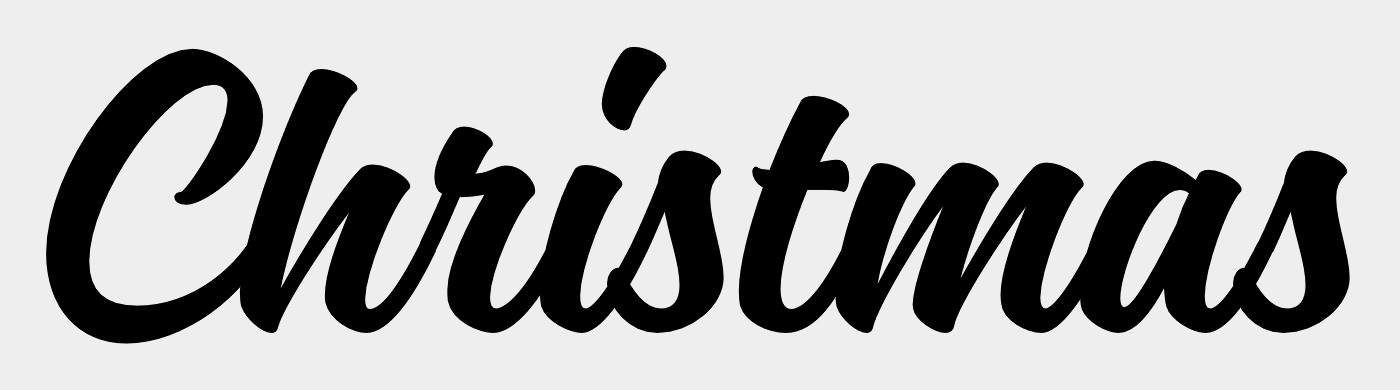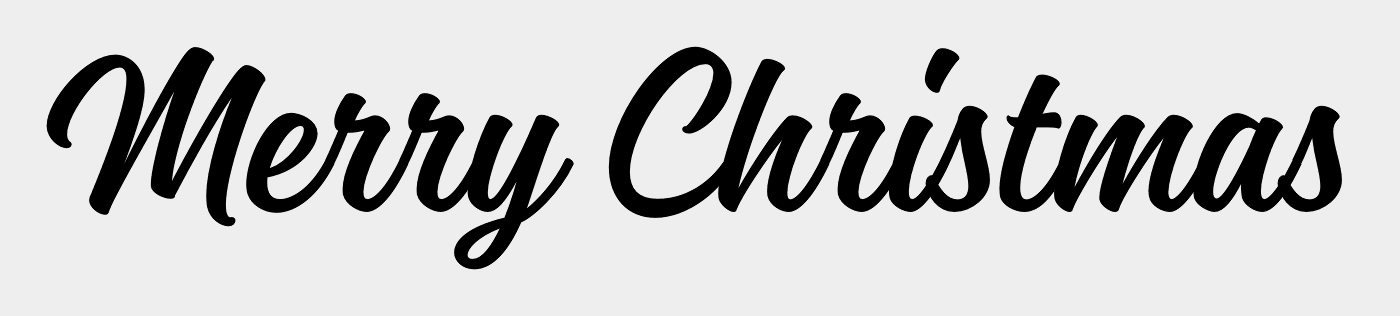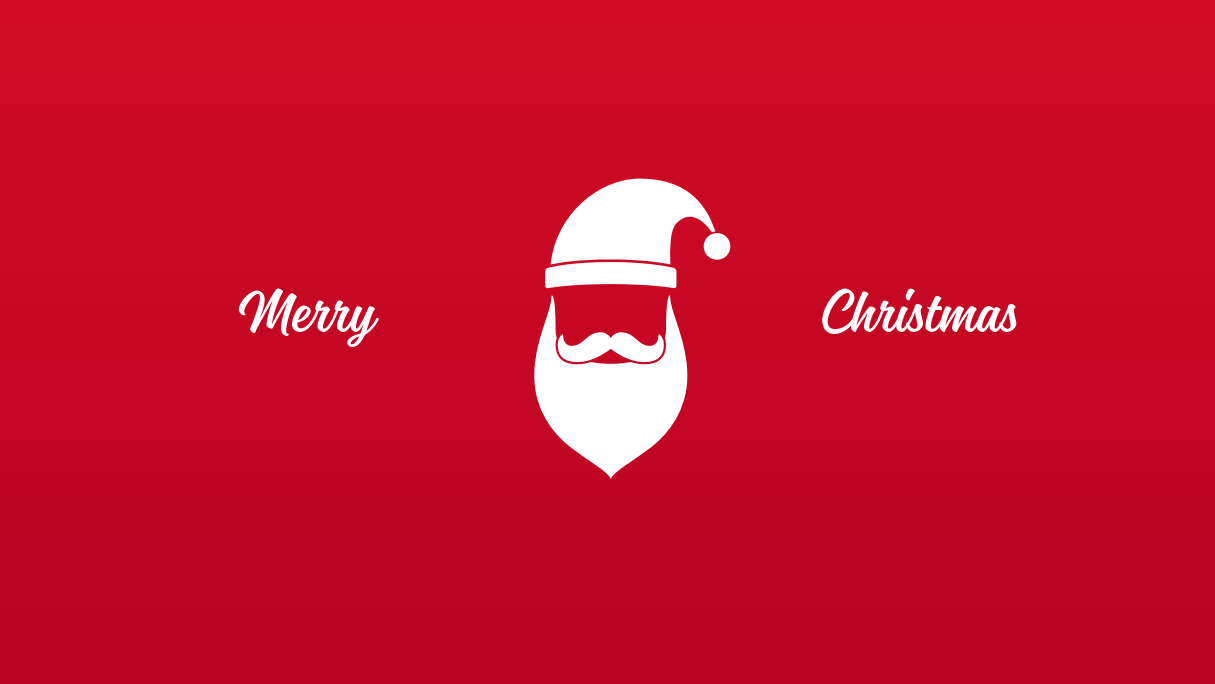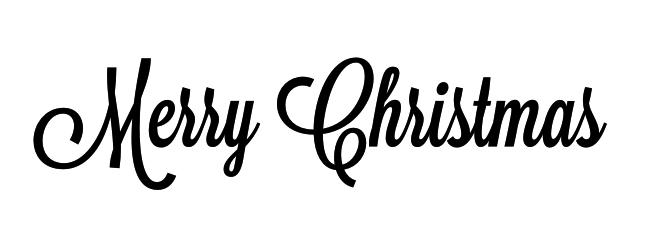
Weihnachts-Font Viktor Script (Alternativen)
Ich bin gerade verzweifelt auf der Suche nach einem ähnlichen Font zur Viktor Script.
Kennt jemand von euch gute (kostenlose) Alternativen zur Viktor-Script im ähnlichen Schreibstil :-??
Ich könnte ja mal wieder Frau Worthington ins Spiel bringen: https://www.fontsquirrel.com/fonts/milkshake
Ist allerdings etwas breiter …
Ansonsten findet man solche Schriften doch gerade wie Sand am Meer :-?
Warum passt denn die Viktor nicht, bzw. wozu Alternativen?
Ich habe bis jetzt noch keine passende bzw. gute Alternative gefunden :-(.
Passt etwas in dieser Art?
„Lavanderia“ bei LostType (Pay what You want) gibts in 3 Stärken.
Die Lavenderia gefällt mir schon ganz gut. Ich habe mal bei LostType weitergeschaut und bin auf die Mission Script gestoßen, die mir noch einen Tick besser gefällt:
Darunter auch:
Ich hab mir die Slanted Variante jetzt mal gegönnt :nicken: (auch wenn ich mit der Mission Script schon ganz zufrieden war).
Falls sonst noch jemand auf der Suche ist (und dIeR PartnerIn Schriftkäufe für Privatanwendungnen strikt verbietet :cry:) hätte ich hier noch 2 Kandidaten, die etwa in die Richtung gehen, die erste sogar von einem Forumskollegen.
Praegefest
Dancing Script
Da sie schon einen passenden Namen hat (und Anfang diese Woche auf fontsquirrel veröffentlicht wurde) möchte ich für zukünftige Suchende die Cookie nicht unerwähnt lassen :-D